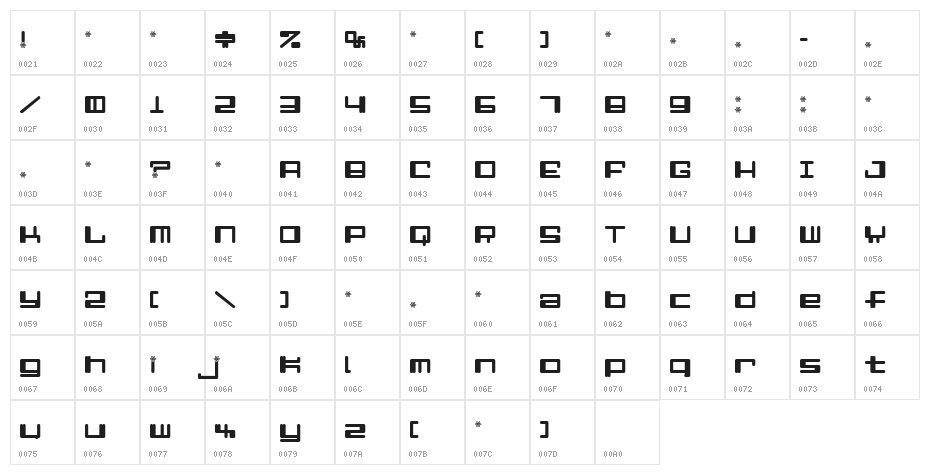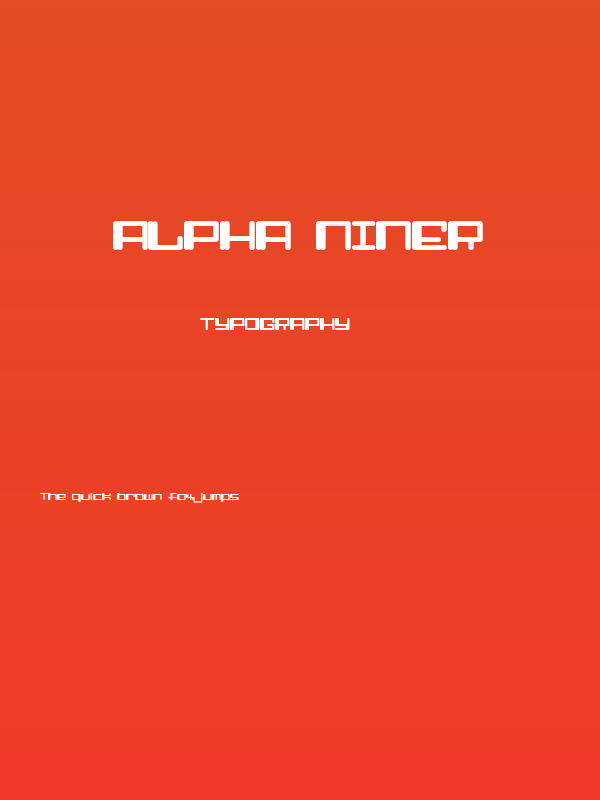
Alpha Niner Font
| Caso d'uso | Logos, Headlines, Digital Interfaces |
| Progetti proposti | Ideal for tech branding, digital interfaces, video game design, and futuristic-themed projects. |